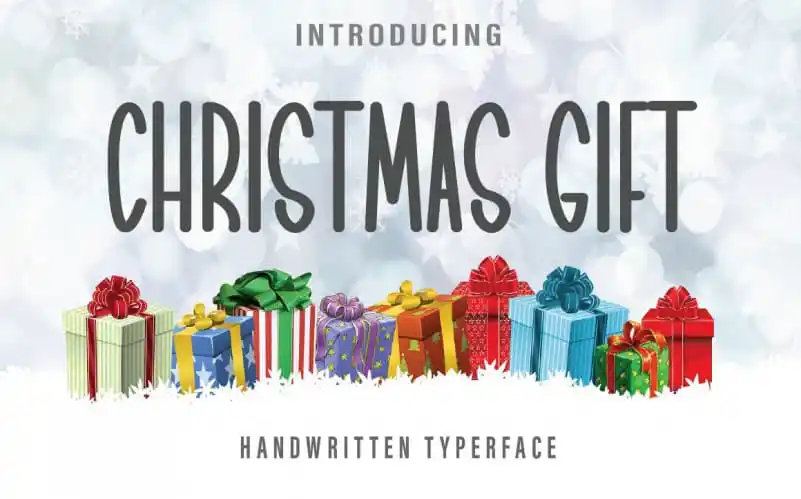
Christmas Gift Display Font – Download Grátis
A fonte ‘Christmas Gift Display Font’ é uma escolha perfeita para decorar seu Natal com estilo. Criada pela incrível equipe do Farz Studio, esta fonte é um encantador conjunto de letras à mão escrita que traz consigo a pureza e simplicidade de um desenho à mão. Convidativo e enérgico, ela não apenas ajuda a tornar seus projetos natalinos mais alegres, mas também lhes dá um toque único e pessoal. Perfeita para gráficos como cartões personalizados, letras em arranjos de árvores de Natal ou até mesmo no layout de sites e blogs natalinos. Este estilo elegante e charmoso é perfeito para capturar a magia do período festivo, proporcionando um visual encantador sem precisar recorrer a muitos recursos digitais complexos. Com seu design leve e simples, ‘Christmas Gift Display Font’ é uma adição divertida ao seu arsenal de fontes que certamente tornará seus projetos natalinos ainda mais especiais.